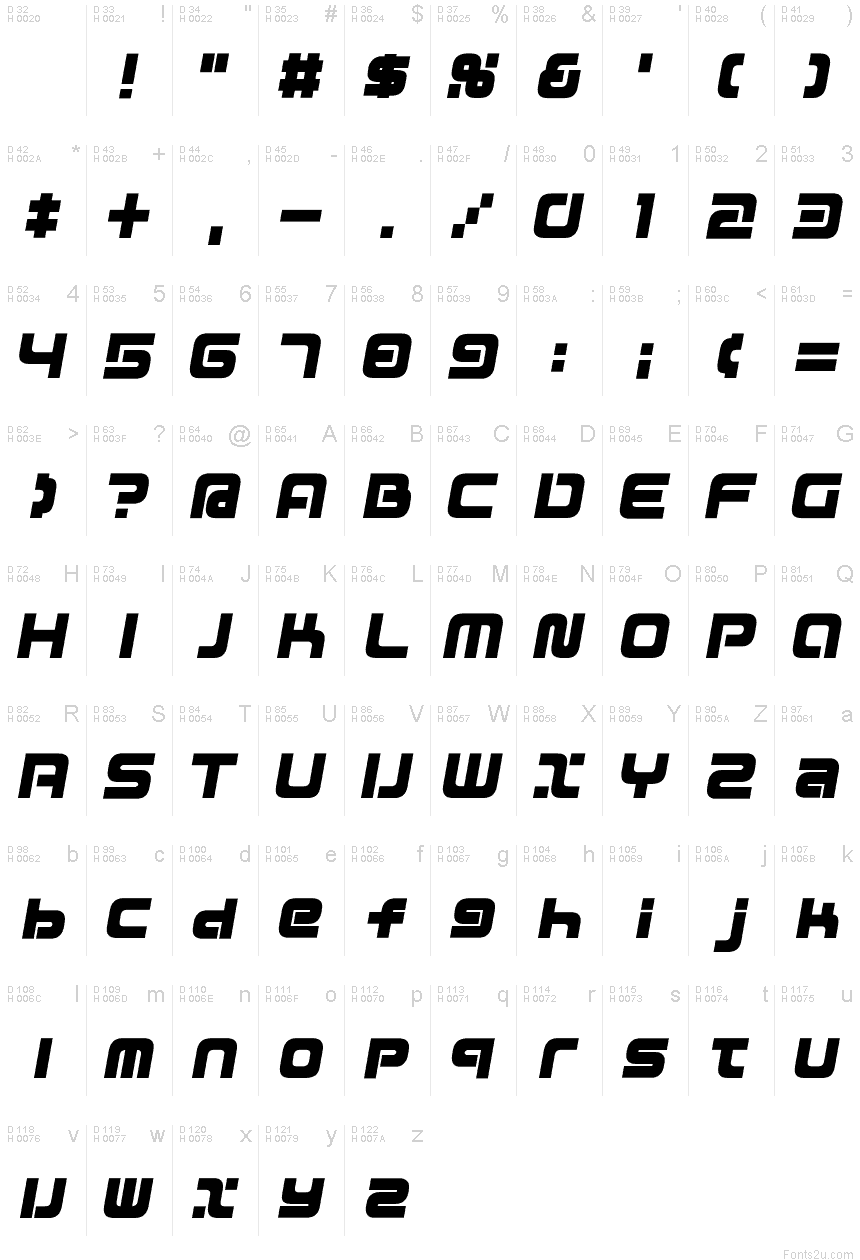
D3 Mouldism Round Italic
Krój D3 Mouldism Round Italic od Yoshiyasu Ito / DigitalDreamDesign stawia na elegancki, zaokrąglony styl techno. Dzięki grubym, czarnym kształtom i dynamicznemu pochyleniu sprawia wrażenie stworzonego do ruchu. Wąskie krzywizny i kwadratowe kontury nadają mu gładką, uformowaną strukturę, która pozostaje wyraźna nawet przy szybkim spojrzeniu. Krój dostępny jest za darmo do śmiałych, futurystycznych projektów.
Ten darmowy font świetnie sprawdza się tam, gdzie potrzebujesz energicznej, technologicznej typografii: w logotypach gier, tytułach sci-fi, brandingu e-sportowym, ekranach startowych aplikacji, plakatach eventowych czy nakładkach do streamingu. D3 Mouldism Round Italic najlepiej prezentuje się w dużych rozmiarach i dobrze łączy się z prostym, neutralnym bezszeryfowym krojem w tekstach pomocniczych, pozwalając swoim masywnym, ukośnym formom robić największe wrażenie.